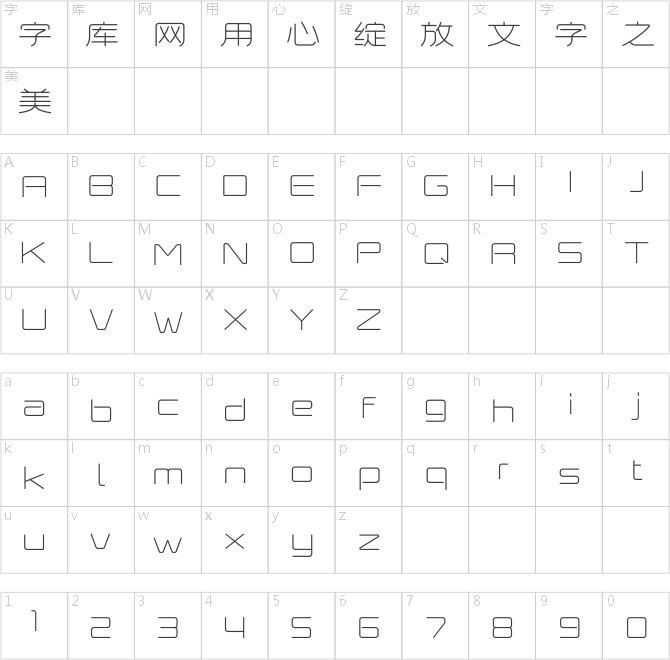
字体名称: 方正秋刀鱼润黑
方正秋刀鱼润黑
作者秋刀鱼,本名姜鹏飞,这款字体的灵感来自于一首古诗《相思》,意在表现一种传统委婉的情感,作者早些年做过一篇字体设计帖子,以文字与海报的形式结合,去体现传统之美。后来经过不断尝试与优化,最终确定将它做成一套完整的字库,其字为黑体大形,结构宽扁,重心平稳,笔画纤细温润,给人典雅平和的感觉,故取名润黑体,一些笔画的设计参考隶书的感觉,整体有传统古朴的韵味。